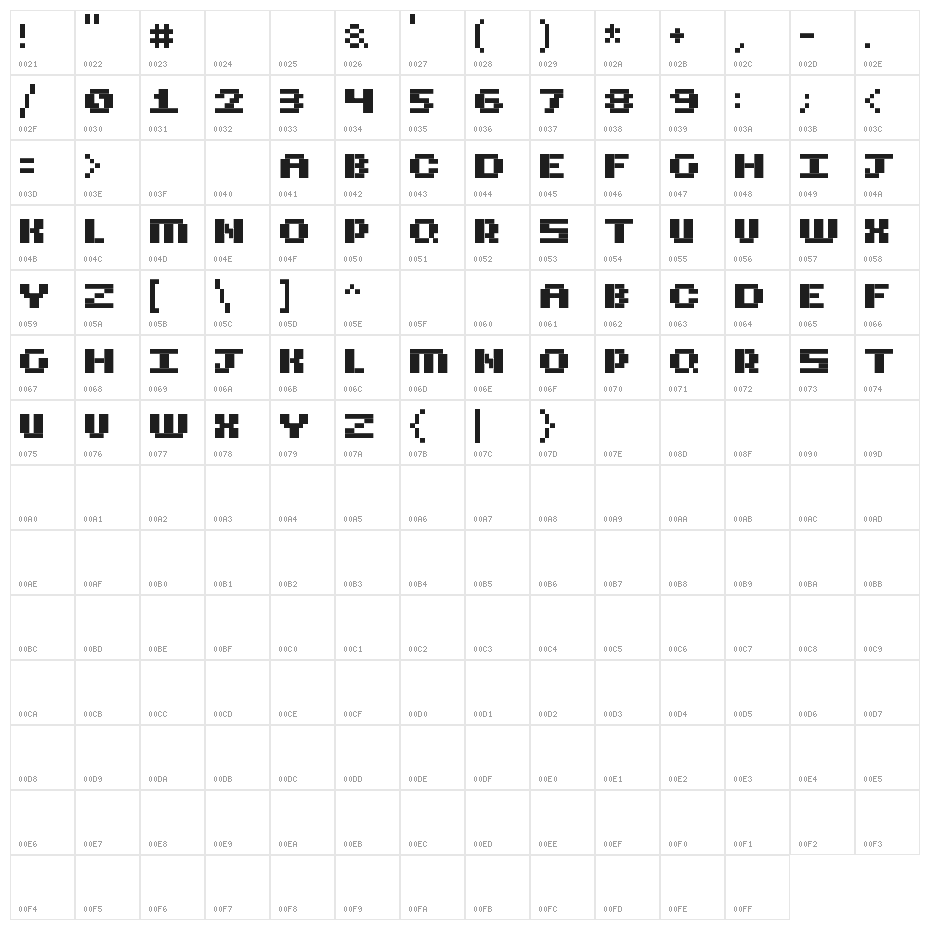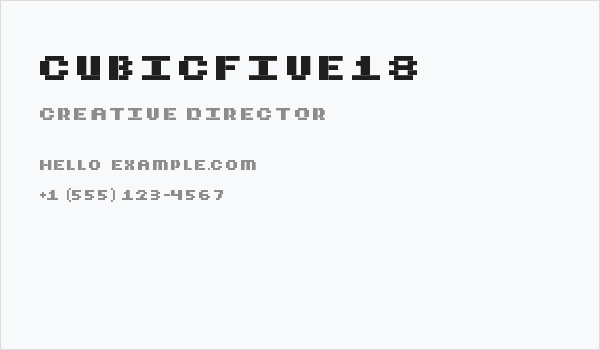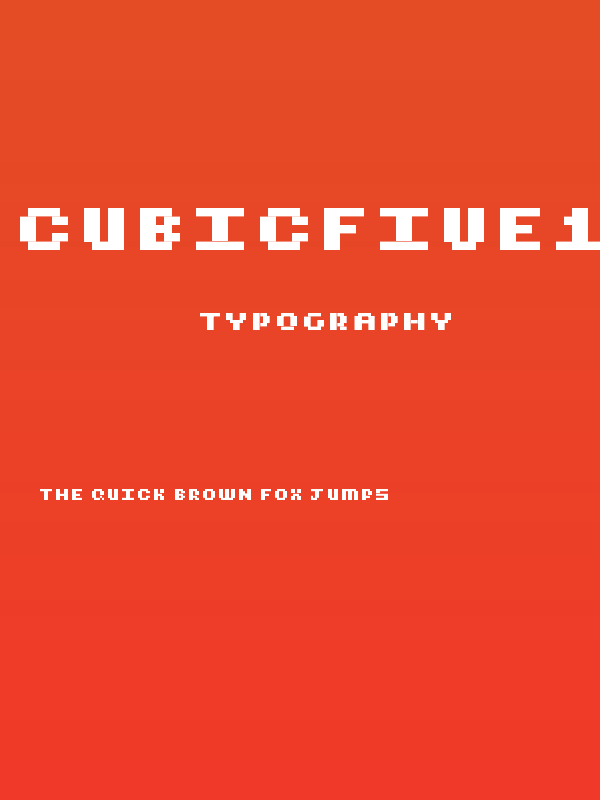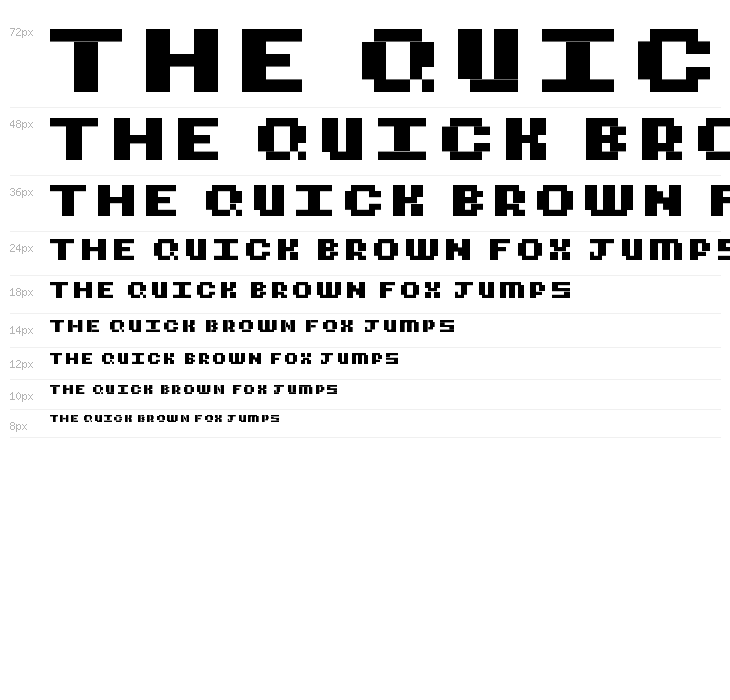
CubicFive18 Font
| Gesamtstil | Retro, Digital |
| Anwendungsfall | Headlines, Logos, Digital Art |
| Vorgeschlagene Projekte | Ideal for video game graphics, tech-themed posters, retro branding, and digital art projects. |